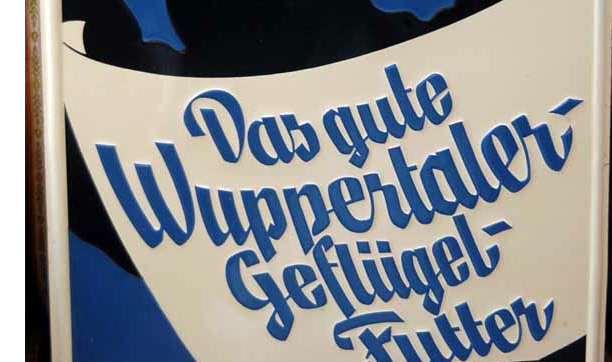
Schriften aus den 50er Jahren?
Hallo ich suche Schriften aus den 50er Jahren wie z.B. diese hier.
Da ich kein Profi bin fällt es mir schwer zu differenzieren.
Das ist keine Satzschrift, sondern von einem Grafiker gezeichnet. Im unteren Beispiel kannst du das schon daran erkennen, dass jedes kleine e anders aussieht und die Form der jeweiligen Verbindung der Buchstaben geschuldet ist.
Es war übrigens bis in die 1970er Jahre durchaus üblich, dass Ladenschilder, Hausanschriften und großflächige Werbung an frei sichtbaren Brandmauern, Fahrzeugbeschriftungen, Texte auf Ansichtskarten, Glückwunsch und Trauerkarten, Leuchtreklame und was sonst so an schriftlichem nicht auf Papier gedruckt zu sehen war, ja selbst Verkehrsmittelwerbung von Grafikern, Malern (speziell Schildermalern) und Lackierern von Hand geschrieben oder gezeichnet waren.
Mein Onkel (Gustav Peyk) hat damit, als Grafiker seinen Lebensunterhalt bestritten, indem er schriftliche Glückwunsch, Familienfeier-  oder Trauerkarten entwarf, und Lackierer mussten die freie Beschriftung von Fahrzeugen, mit selbst vorgezeichneten Beschriftungen, die mittels Stanniol-Folie auf den Lack übertragen wurde noch regulär lernen.